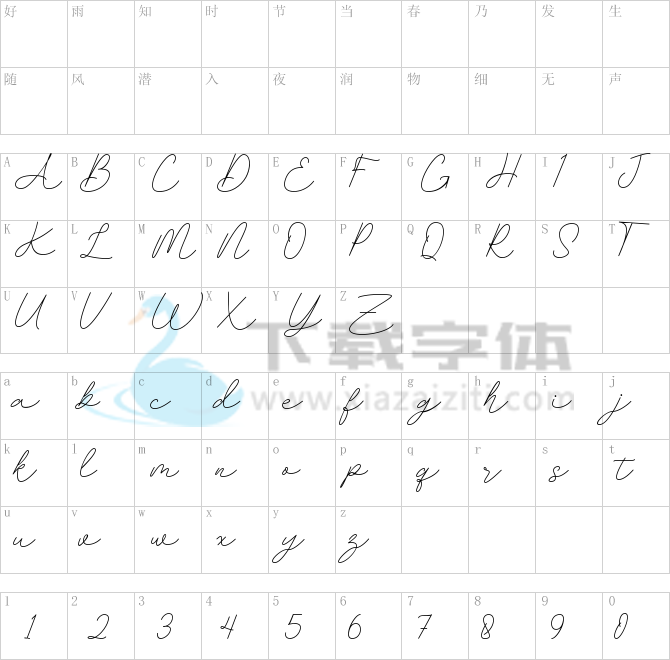
Apollo Butler.ttf字体下载
Apollo Butler.ttf字体下载,这款字体结构工整、笔画清晰,兼顾美观与易读性,适用于标题、正文、海报、包装、LOGO 等多种场景。字形优雅稳定,风格百搭耐看,适配日常排版与创意设计,让文字呈现更舒适、更具质感。Apollo Butler.ttf字体下载一笔一画,皆是细节,以均衡的比例、流畅的线条打造舒适视觉体验,字形端正大气,风格简约现代。无论是商业设计、品牌宣传还是日常排版,都能轻松驾驭,让文字更有格调与力量。Apollo Butler.ttf字体下载字体下载。